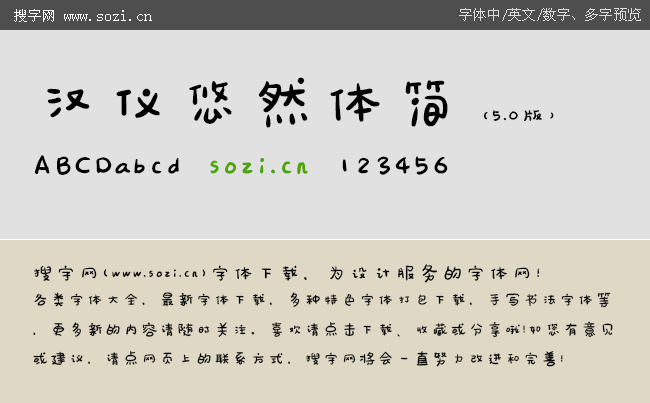
漢儀悠然體簡
搜字網(wǎng)給大家提供的一款純手寫中文字體下載漢儀悠然體,字如其名,字體在注重隨性、閑適的同時,又不失俏皮的一面。其中有些多筆畫字體的結(jié)構(gòu)變形更形成了自己獨特的藝術(shù)風(fēng)格。字體最顯著的特征之一是字體的“口”部及點均使用圈和圓代替;并且筆畫之間透出的可愛、隨性,更為字體增添了幾分魅力。悠然體適合用于插畫及漫畫作品,搭配攝影作品的圖文效果也十分出色。是漢儀公司又一受歡迎中文字體。